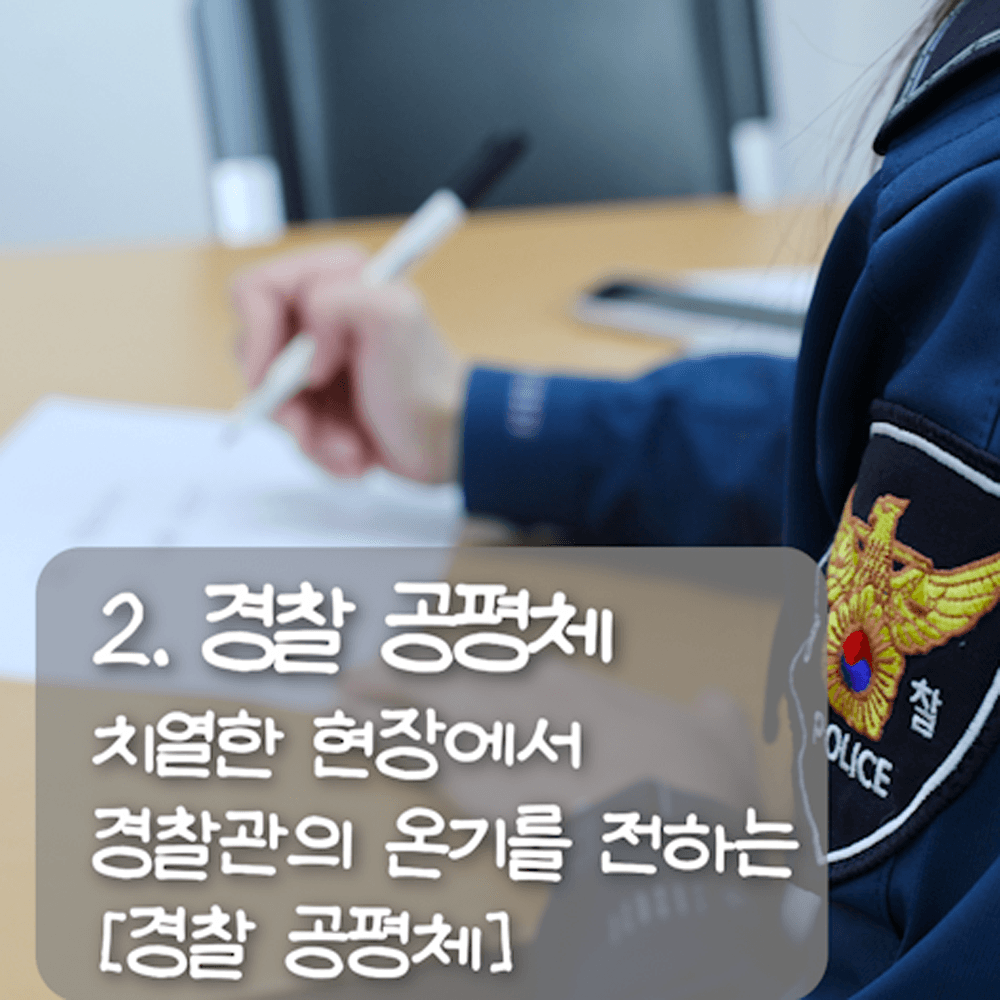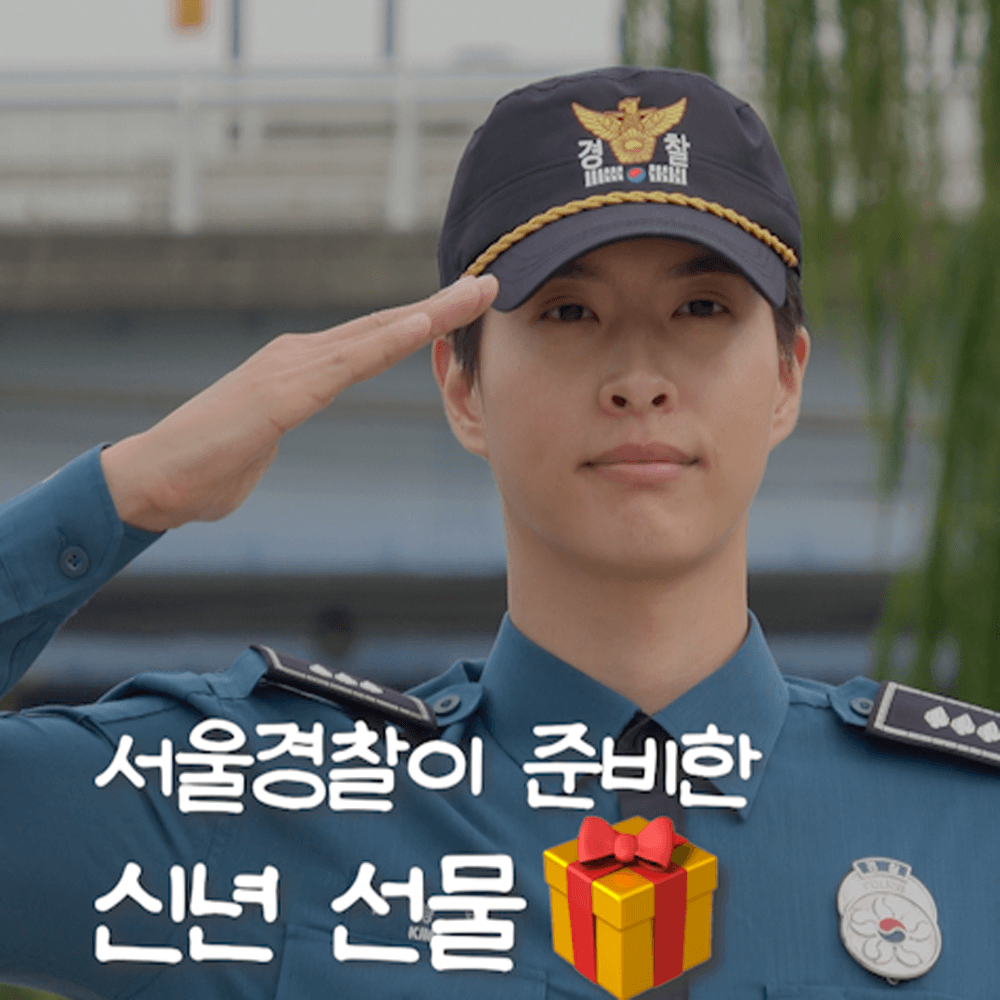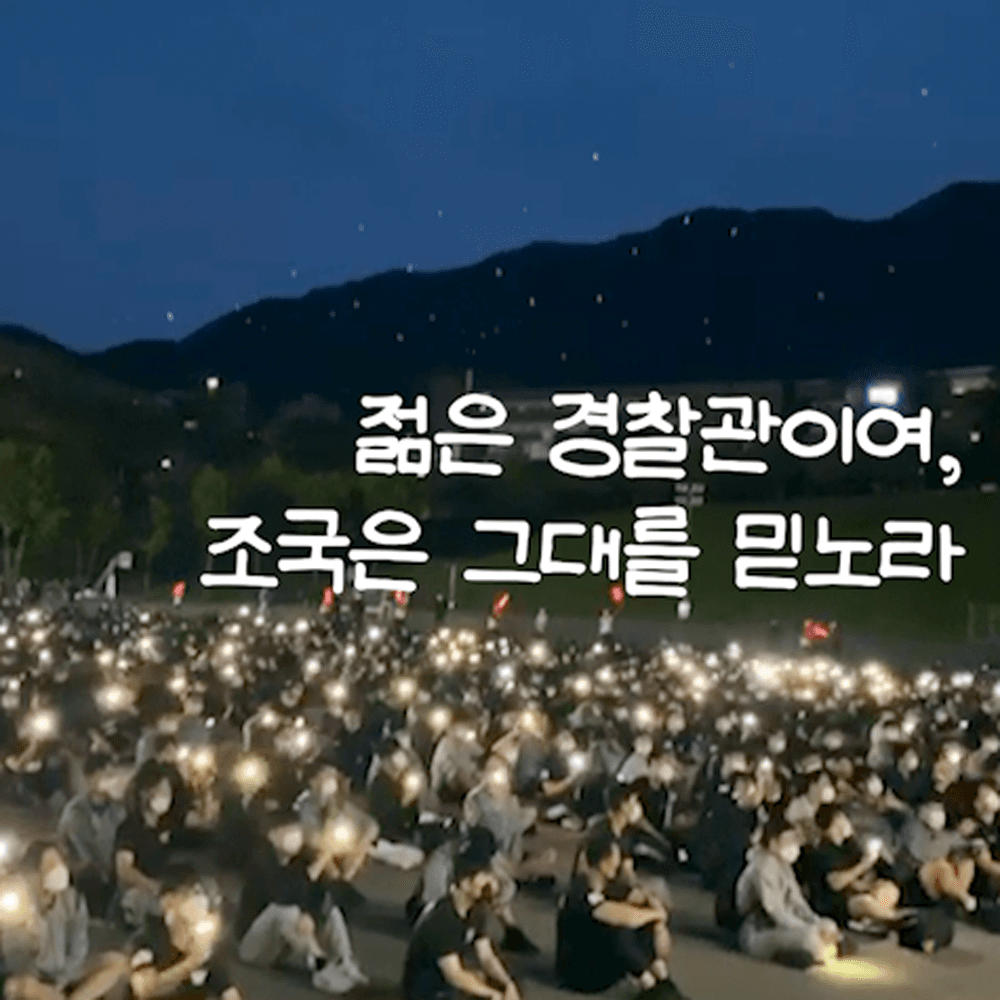
그리운 경찰공평체
Griun PolFairness
그리운 경찰공평체 소개
‘그리운 경찰공평체’는 아기자기한 느낌이 물씬 묻어나는 친숙한 인상의 폰트입니다. 서울경찰 「인권손글씨 공모전」에 수상작으로 선정된 경찰공평체는 새내기 경찰관이 작성한 풋풋한 느낌의 손글씨인데요, 다양한 삶 속에서 마주하는 공정한 경찰의 이미지를 표현하고자 공평체라는 폰트명으로 제작되었습니다. 우리 모두 힘을 합쳐 공정과 상식이 통하는 세상을 만들고, 정의로운 사회로 발돋움하는데 활용되어지길 소망합니다.